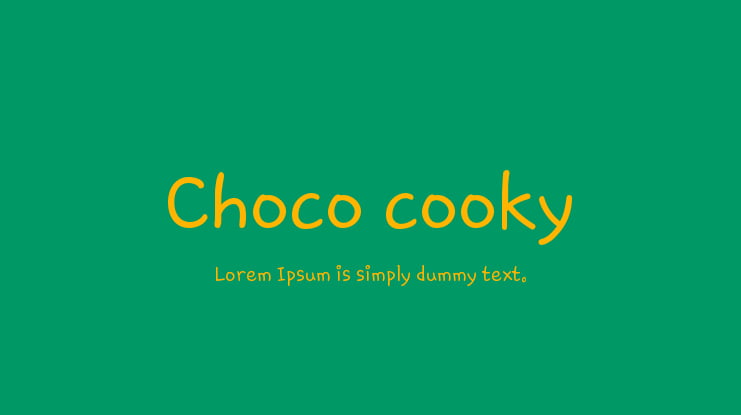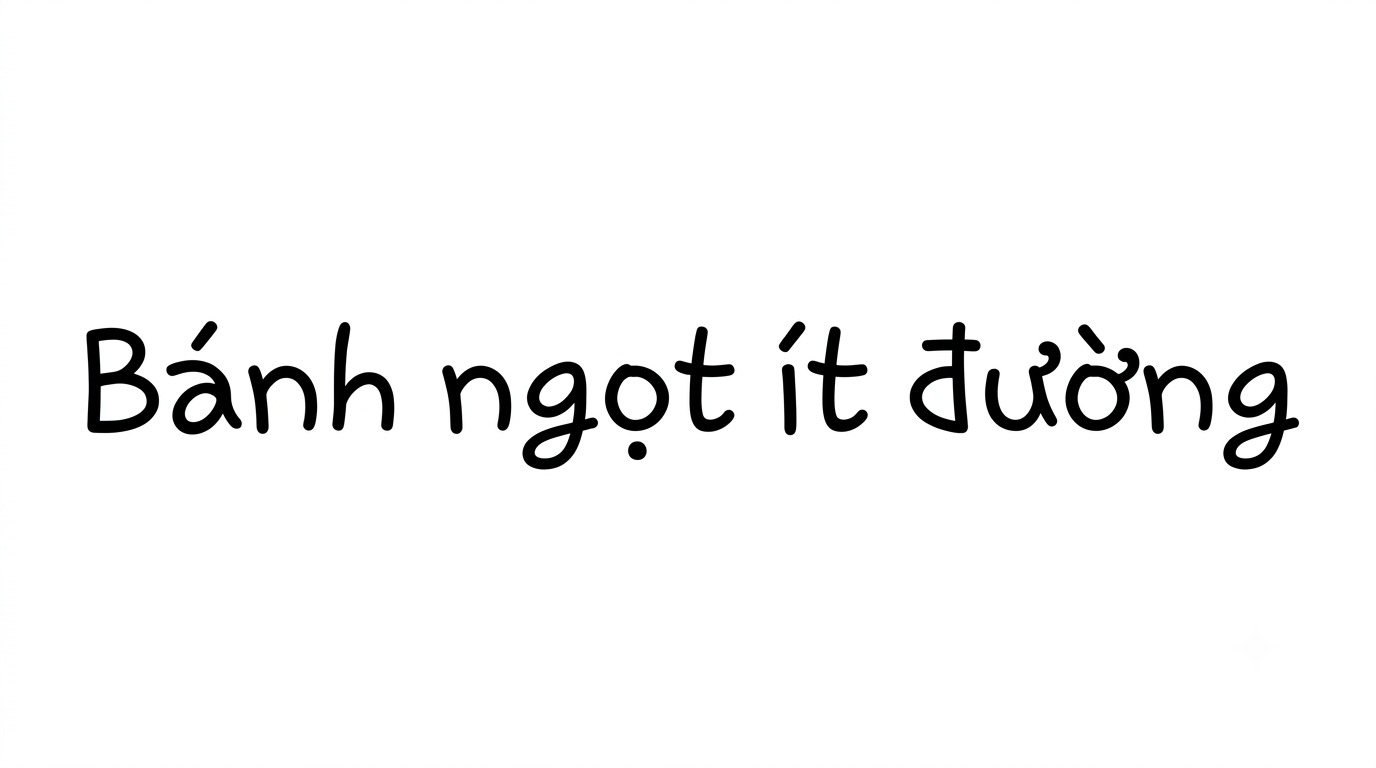
Nhiều nhà thiết kế khi sử dụng font Chococooky thường gặp tình trạng lỗi dấu tiếng Việt, ký tự hiển thị chưa cân đối hoặc đường nét bị răng cưa khi phóng lớn để in trên tem nhãn, hộp quà và sản phẩm dành cho trẻ em. Những lỗi kỹ thuật này có thể làm giảm sự sinh động của thiết kế, khiến bao bì thiếu đi nét đáng yêu và sự chuyên nghiệp cần có.
Font chữ Chococooky là gì?
Font chữ Choco cooky là một phông chữ thuộc dòng Handwritten (viết tay) vô cùng nổi tiếng, ban đầu được biết đến rộng rãi thông qua các thiết kế giao diện trên điện thoại thông minh. Đặc trưng của bộ chữ này là các đường nét bo tròn, dày dặn và mang phong cách ngộ nghĩnh, đáng yêu như những viên kẹo ngọt. Với cấu trúc ký tự không quá gò bó, Choco cooky mang lại cảm giác vui vẻ, thân thiện và giàu năng lượng, rất phù hợp cho các dự án hướng đến đối tượng trẻ em hoặc các ngành hàng thực phẩm, đồ uống.
Sức hút của phông chữ này không chỉ nằm ở tính ứng dụng trên màn hình kỹ thuật số mà còn ở khả năng tạo điểm nhấn cho các ấn phẩm in ấn thực tế. Tuy nhiên, bản gốc thường không hỗ trợ đầy đủ bộ gõ tiếng Việt, dẫn đến việc các dấu thanh bị lệch vị trí hoặc không đồng nhất. Bản việt hóa được chia sẻ đã xử lý kỹ lưỡng Kerning và dấu mũ, giúp các designer tự tin ứng dụng trên nhiều chất liệu từ túi giấy, hộp cứng đến các bề mặt gốm sứ hay vải canvas mà vẫn giữ được tinh thần nguyên bản của bộ chữ.
6 ứng dụng của font Chococooky trong thiết kế và in ấn
Nhờ phong cách tròn trịa, vui nhộn và gần gũi, font Chococooky Việt hóa phù hợp với các thiết kế hướng đến trẻ em, sản phẩm gia đình và quà tặng doanh nghiệp mang tính sáng tạo:
- Thiết kế bao bì bánh kẹo và đồ ăn nhẹ: Nét chữ mềm mại của Chococooky phù hợp để in tên sản phẩm trên hộp giấy, túi bánh hoặc hũ kẹo. Khi kết hợp cùng màu sắc tươi sáng, font chữ giúp bao bì tạo cảm giác thân thiện với trẻ nhỏ.
- Sản xuất nhãn vở và sticker cho bé: Chococooky được ứng dụng trong thiết kế nhãn tên học sinh, sticker trang trí đồ dùng cá nhân hoặc tem khen thưởng. In Viva hỗ trợ gia công bế theo hình dáng riêng, giúp sản phẩm có tính thẩm mỹ cao hơn.
- Trang trí hộp quà sinh nhật thiếu nhi: Font Chococooky khi in trên hộp giấy Ivory hoặc hộp quà nhỏ giúp tạo điểm nhấn cho các sản phẩm dành cho trẻ em, phù hợp với những chương trình tặng quà nội bộ doanh nghiệp.
- In đồng phục lớp và túi vải mầm non: Các câu slogan, tên nhóm hoặc thông điệp ngắn sử dụng Chococooky có thể ứng dụng trong in chuyển nhiệt trên áo thun, túi vải canvas, tạo phong cách trẻ trung và năng động.
- Khắc laser bình nước và quà tặng cá nhân: Logo hoặc tên riêng dùng font Chococooky khi khắc trên nhựa sinh học, gỗ hoặc kim loại giúp sản phẩm mang dấu ấn cá nhân rõ ràng hơn.
- Thiết kế hình ảnh truyền thông ngành Mẹ và Bé: Font chữ này phù hợp cho banner, poster, thiệp chúc mừng hoặc các ấn phẩm quảng bá cần tạo cảm giác vui vẻ, gần gũi với phụ huynh và trẻ nhỏ.
5 lưu ý khi sử dụng font Chococooky trong in ấn
Để font Chococooky hiển thị rõ nét trên thành phẩm thực tế, designer nên chú ý các yếu tố kỹ thuật sau:
- Kiểm soát khoảng cách ký tự (Kerning): Chococooky có cấu trúc chữ tròn và khoảng cách giữa các ký tự khá gần. Khi thiết kế tiêu đề dài hoặc in trên bề mặt cong như bình nước, nên điều chỉnh Kerning thủ công để chữ không bị dính vào nhau.
- Tối ưu đường Path khi gia công bế nổi: Khi sử dụng Chococooky để dập nổi logo trên hộp quà, cần xử lý các điểm neo bo tròn trong file vector. Việc này giúp khuôn bế thể hiện đúng đường nét chữ, hạn chế lỗi rách giấy hoặc biến dạng bề mặt bao bì.
- Lựa chọn chất liệu giấy phù hợp: Font Chococooky có nét chữ dày, phù hợp với các bề mặt phẳng như giấy Ivory, Couche hoặc giấy mỹ thuật có độ mịn cao. Với giấy có bề mặt quá thô, các khoảng trống nhỏ trong chữ có thể bị ảnh hưởng khi in.
- Thiết lập hệ màu CMYK phù hợp: Các thiết kế dành cho trẻ em thường sử dụng màu sắc tươi sáng. Designer nên kiểm tra hệ màu CMYK trước khi in để màu sắc trên bao bì và tem nhãn có sự tương đồng với bản thiết kế.